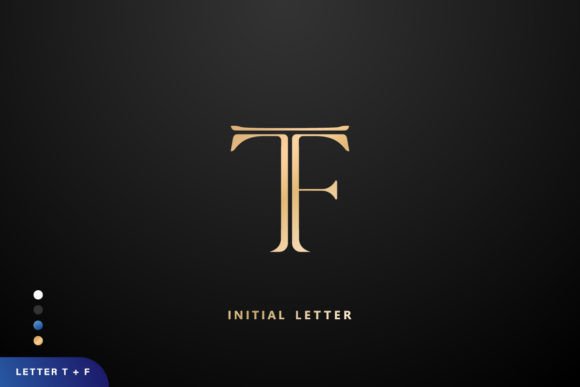
TF Initial Letters Monogram Logotypes
์ •๋ฐ€ํ•˜๊ฒŒ ์ œ์ž‘๋œ TF Initial Letters Monogram Logotypes๋Š” ๊น”๋”ํ•œ ๋ฒกํ„ฐ, ๋ถ€๋“œ๋Ÿฌ์šด ํƒ€์ดํฌ๊ทธ๋ž˜ํ”ผ ๋ฐ ์•ˆ์‹ฌํ•  ์ˆ˜ ์žˆ๋Š” ์ƒ์—…์šฉ ๋ผ์ด์„ ์Šค๋ฅผ ์ œ๊ณตํ•ฉ๋‹ˆ๋‹ค.